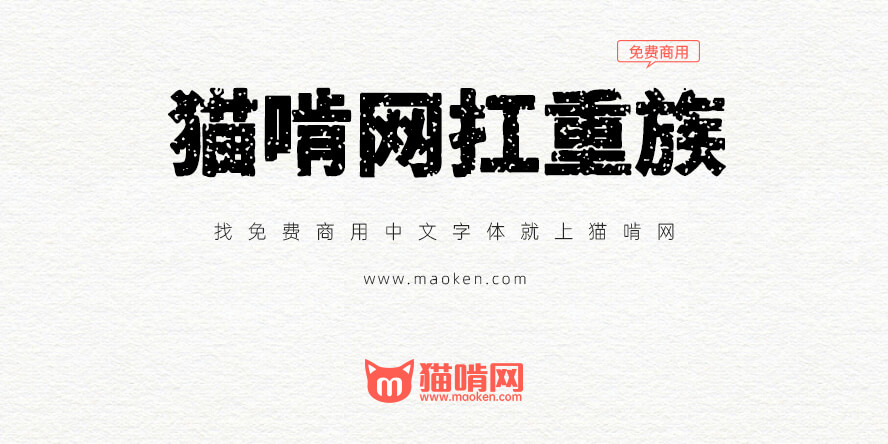
猫啃网扛重族黑:一款很烂的免费商用中文字体 基于思源黑体改造
猫啃网扛重族系列字体是马来西亚网友@夜煞之乐友情制作,猫啃网倾情冠名的免费商用字休。猫啃网扛重族系列包括了两款字体,一款是基于思源黑体打烂的黑体,另一款是基于思源宋体打烂的宋体。扛重族宋体已于2021年07月11日制作完成并发布,如有兴趣可以点击这里查看。
猫啃网扛重族黑基于思源黑体改造,通过程序给字体加上破旧斑驳的纹理,满满的复古怀旧风,这是一款适合做大标题的中文字体。至于为什么叫扛重族?根据@夜煞之乐的解释,扛重是打工人的称呼以外,重=字重很重,族=字体家族。
猫啃网扛重族系列的完整版覆盖范围跟思源黑体一样,所以继承了思源字体字数满满的优点,用起来也不太担心缺字少字了。实在是我们这些设计打工人的一大福音。
由于这款字体是通过程序自动处理生成的,所以在某些字形上存在不足之处。而给字体加上破旧斑驳的纹理,使得字体的锚点数急剧增加,字体文件会比较大。所以猫啃君拜托@夜煞之乐把字体分成两个版本,简体版和完整,这两个版本的区别是,简体版的字符范围是GB2312+通用规范汉字表+现代汉语通用字表,所以文件较小。而完整版则跟思源黑体一样范围,简繁也不缺,但文件较大。
一下联想到寂静之地2的海报字 哈哈
举一反三,用脚本生成像“文鼎霹雳体”一样的闪电效果不知是否行得通,这样的字体效果估计更受交欢。
• 这个想法不错,正是缺少可以商用的霹雳体
• 不知道这样算不算抄袭
• 肯定不算啊,字体用的思源黑体,跟他的黑体完全不同的~
• 类似苏新诗古印宋
用在斑驳老旧的设计上,做旧!可以的,收藏着。
好!脚本生成的吗?
• 是的哈~